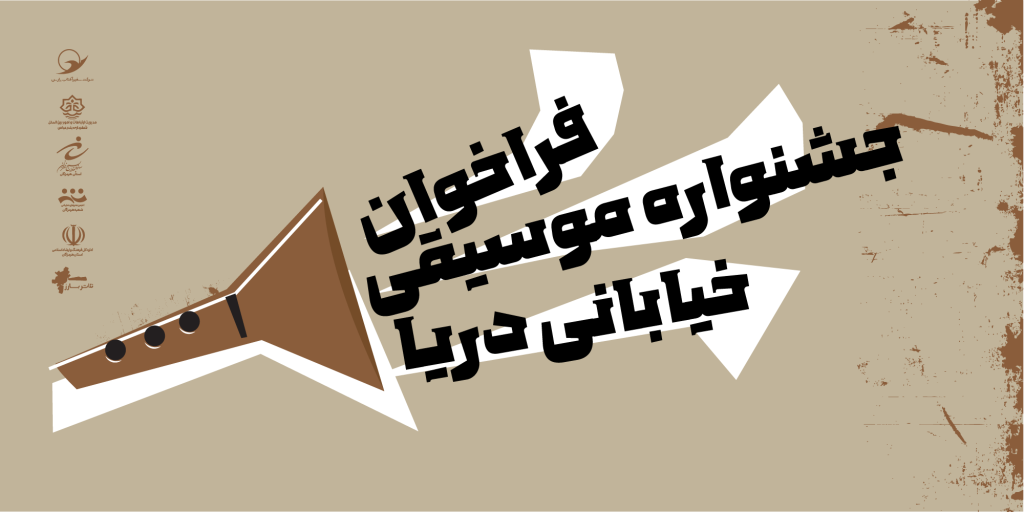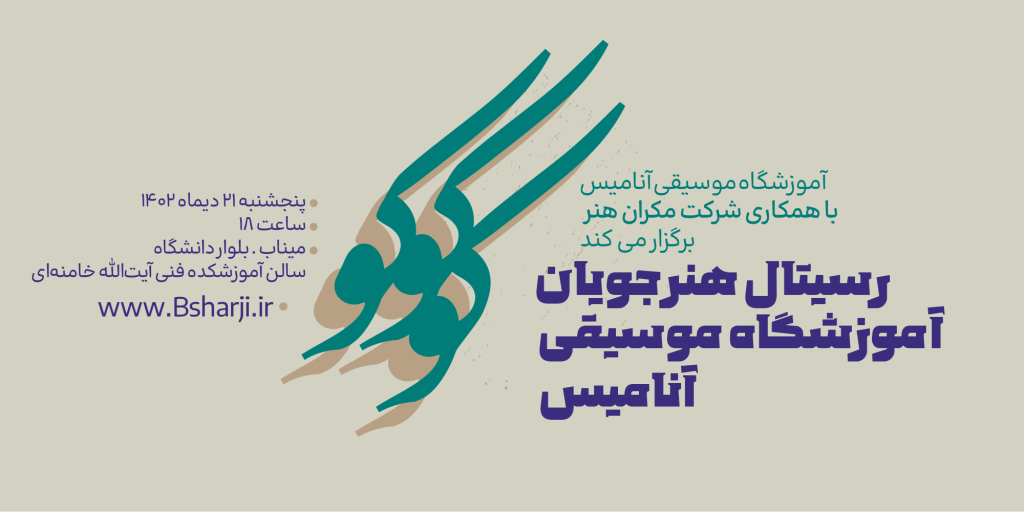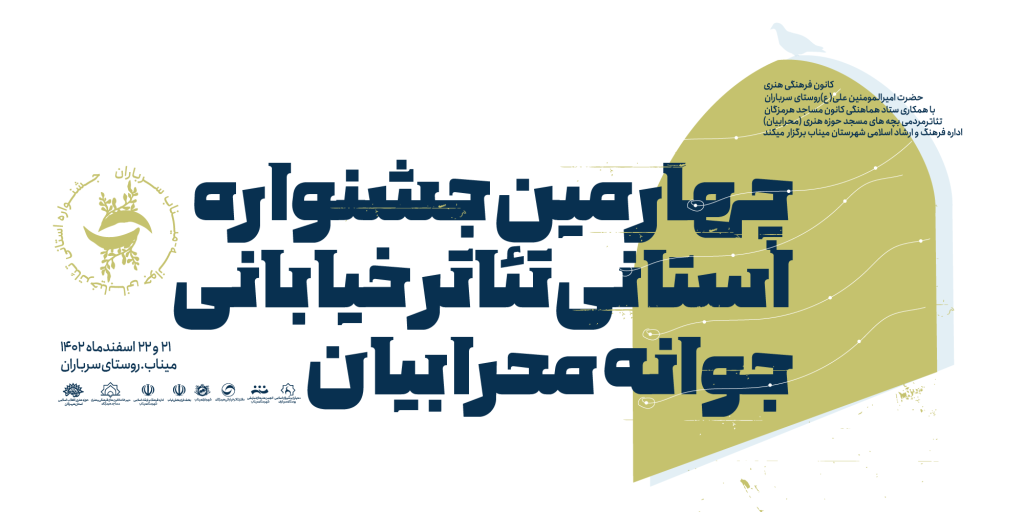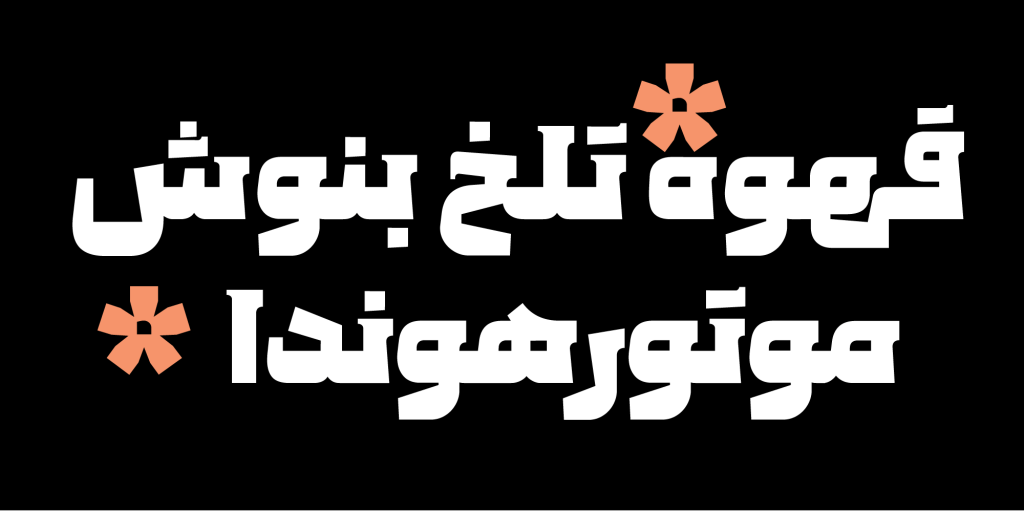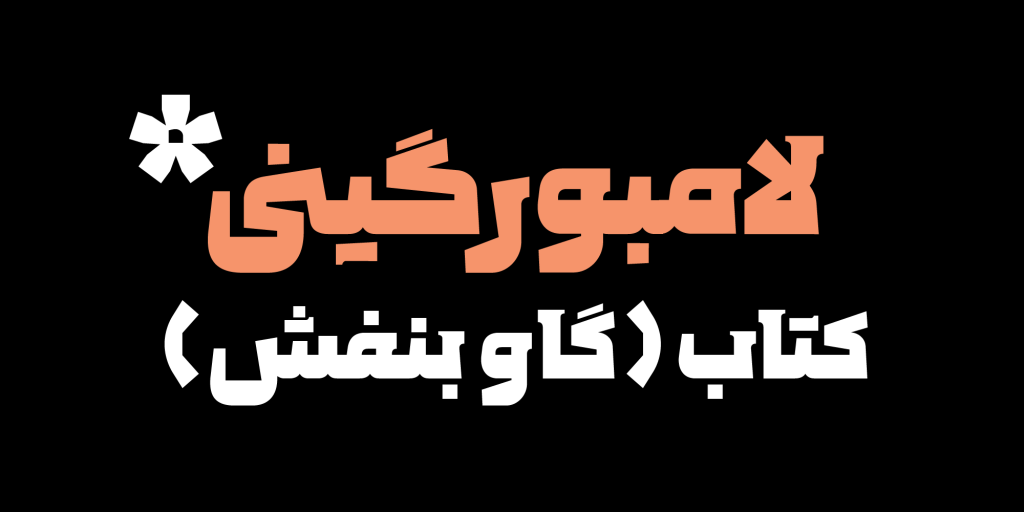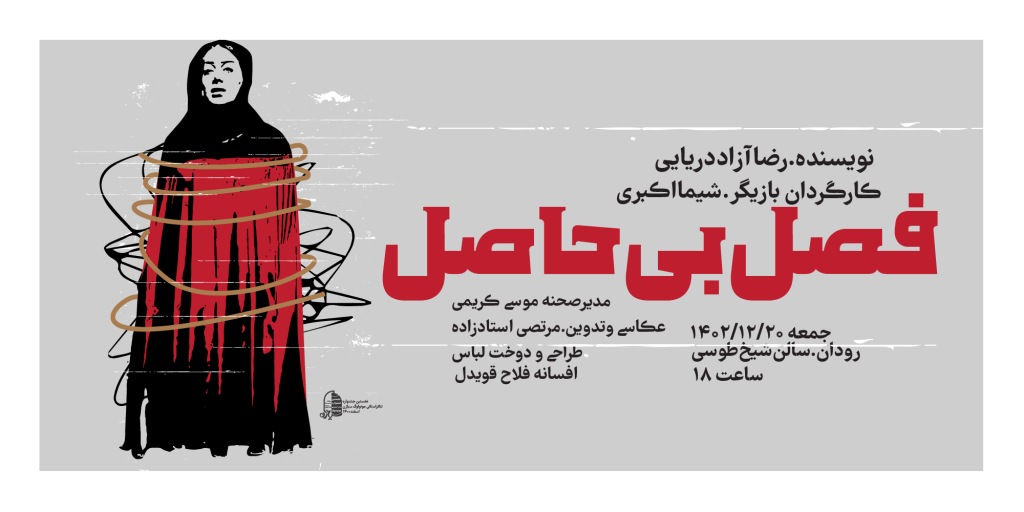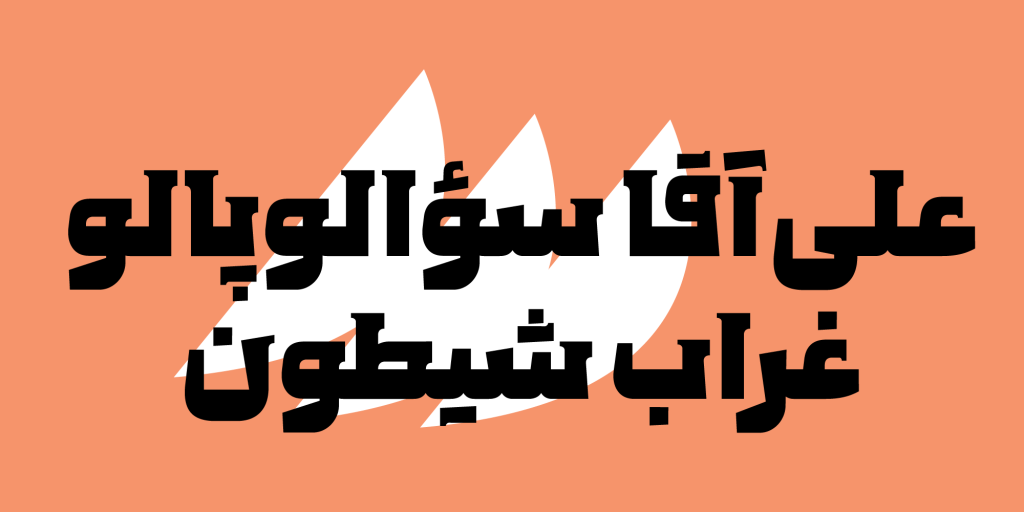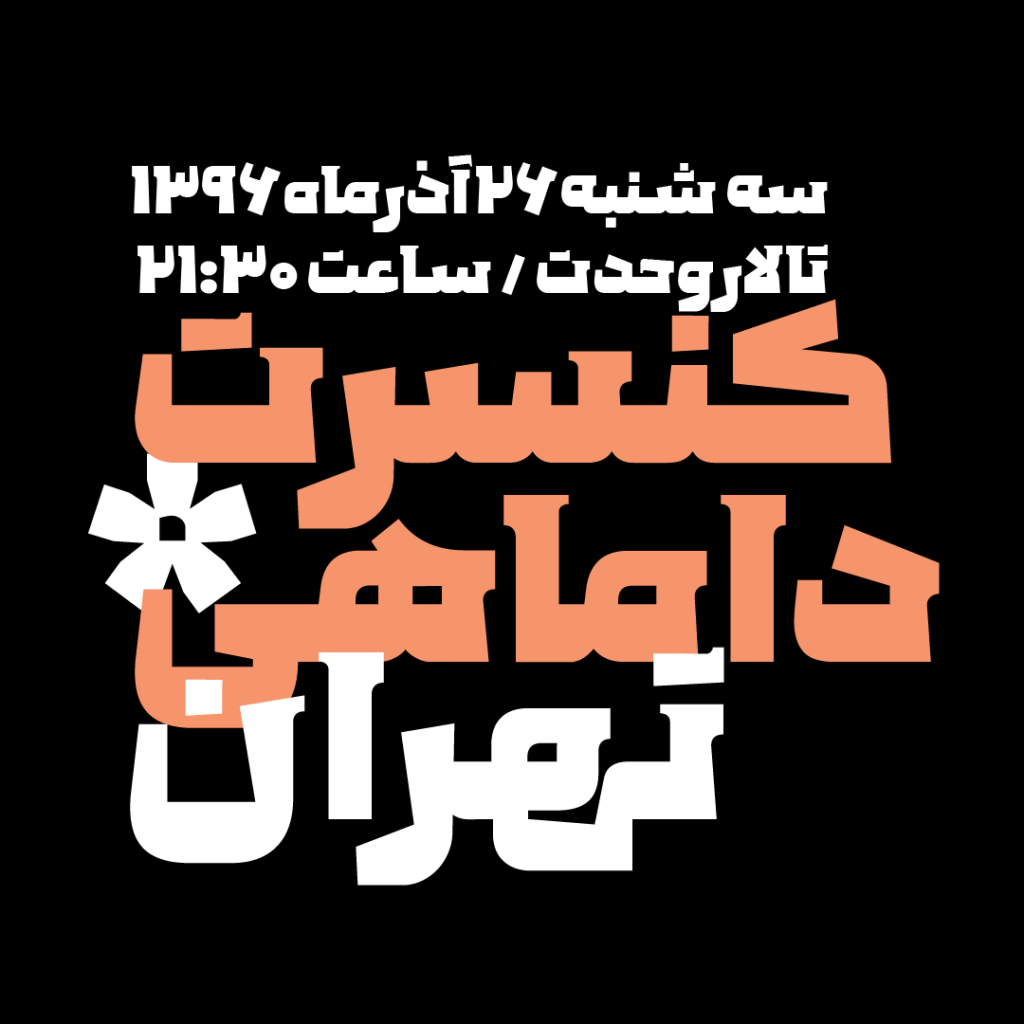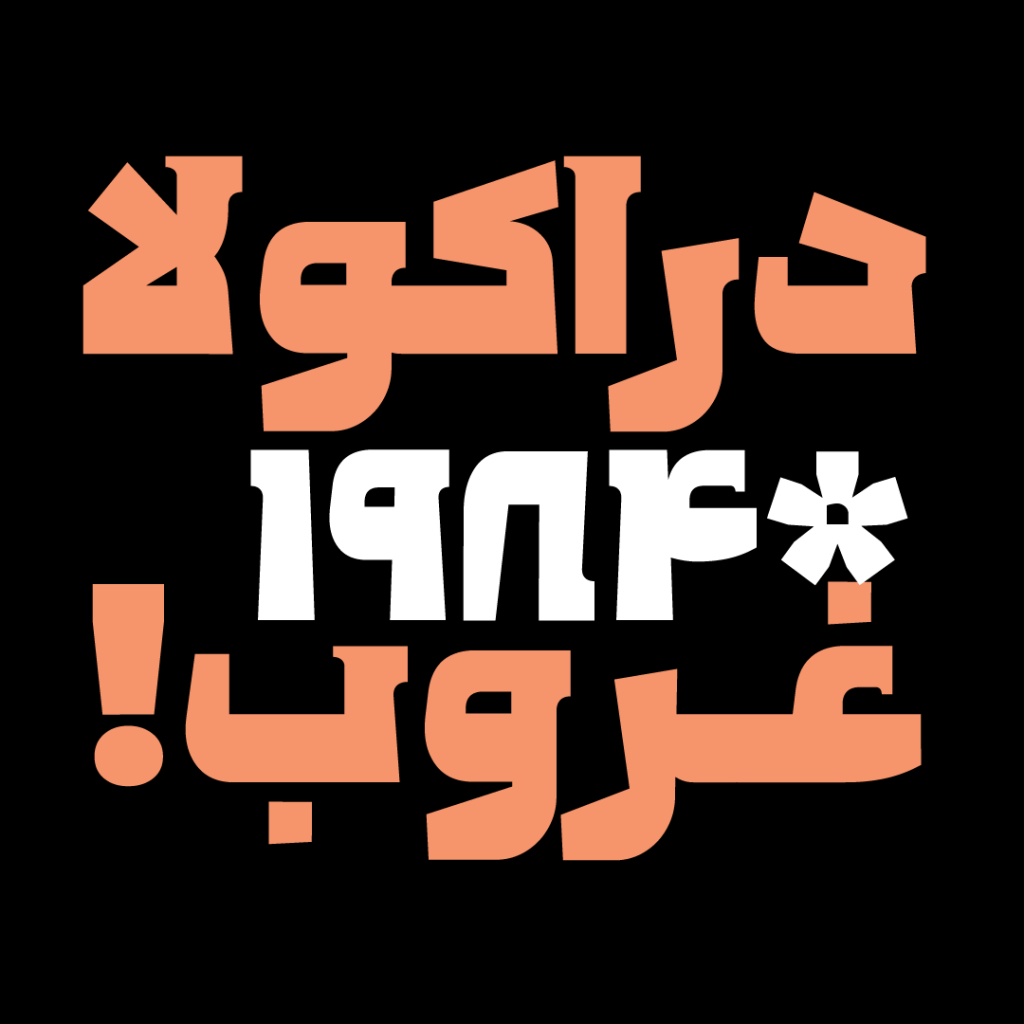
فونت پولاد قلمی نمایشی
فونت پولاد قلمی از خانواده هندسی با پشتیبانی از زبان های مختلف، نماد ها و علائم است. این تایپ فیس مناسب برای متون طولانی و ریز نیست چرا که اساسا برای متون طولانی ساخته و طراحی نشده است. پولاد که شخصیتی جسور و بی باک دارد به دنبال تجربه محیط های مختلف برای جذب نگاه مخاطبین است.
اصولا تایپ فیس پولاد ساخته شده تا در عناوین و تیتر های تبلیغاتی و مطبوعاتی در پوستر ها جلد کتاب ها و مقالات بیلبورد ها و …. خود نمایی کند. این قلم با ساختاری که در فرم حروف خود دارد دارای ویژگی نمایشی بالا است از همین رو جاذبه های لازم را برای دنبال نمودن و خیره کردن نگاه ها به خود در متون کوتاه و عناوین و تیتر ها دارا است.
این قلم با شکستگی هایی که در طراحی فرم های حروف دارد سبب تماییز خود نسبت به سایر فونت ها گردیده و بدین وسیله خودنمایی می کند . نوع طراحی فرم های های آن شباهت به فونت والهالا دارد. والهالا قلمی که خوانایی اولویت اول او نیست و با فرمها و رفتارهای متفاوت حسابی جلبتوجه میکند.
پولاد دارای قابلیت چند زبانی بودن است . این قلم علاوه بر زبان فارسی از زبان های مختلف دیگری همچون عربی، اردو، کوردی پشتیبانی میکند. در قلم پولاد شکل حروف دارای شکستگی و تیزیهای متعدد است . در زیر تصاویری نمونه از این تایپ فیس خاص و منحصر به فرد برای شما عزیزان آماده گردیده است.